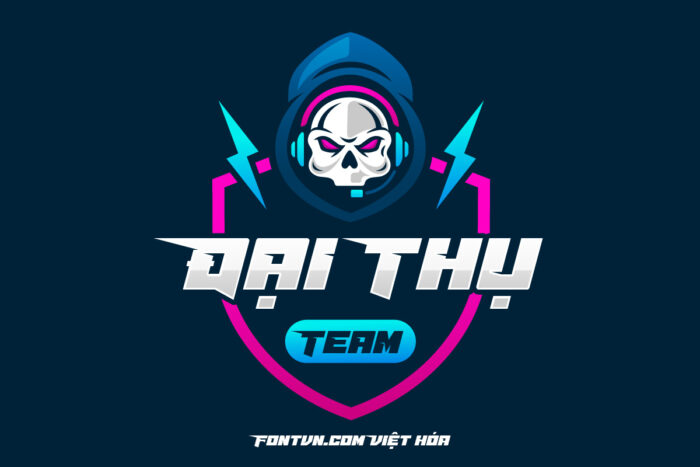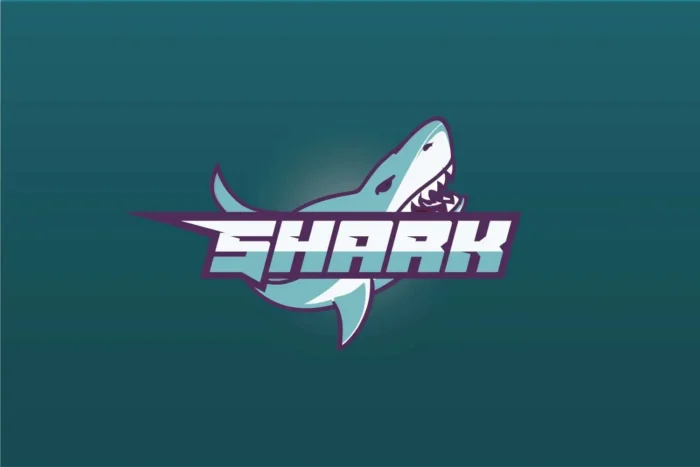
DVN Heroes Việt hóa – Font chữ mạnh mẽ và hiện đại phù hợp logo gaming, truyện tranh
Font chữ DVN Heroes mang đến một cảm giác mạnh mẽ và hiện đại, phù hợp cho các tiêu đề và logo cần sự nổi bật. Đặc trưng của kiểu chữ này là các đường nét sắc bén và góc cạnh, tạo nên sự cứng cáp và quyết đoán. Các ký tự được thiết kế với các khoảng trống và đường cắt táo bạo, giúp chữ trở nên nổi bật và dễ nhận biết.
Ứng dụng của DVN Heroes rất đa dạng, đặc biệt trong các lĩnh vực liên quan đến thể thao, phim hành động, game và truyện tranh siêu anh hùng. Kiểu chữ này có thể được sử dụng cho các tiêu đề báo chí, bìa sách, áp phích quảng cáo và logo thương hiệu. Với sự mạnh mẽ và uy lực, DVN Heroes giúp truyền tải thông điệp mạnh mẽ và quyết liệt, thu hút sự chú ý của người xem ngay lập tức. Ngoài ra, nó cũng thích hợp cho các dự án cần sự sáng tạo và phá cách, đem lại cảm giác hiện đại và năng động.